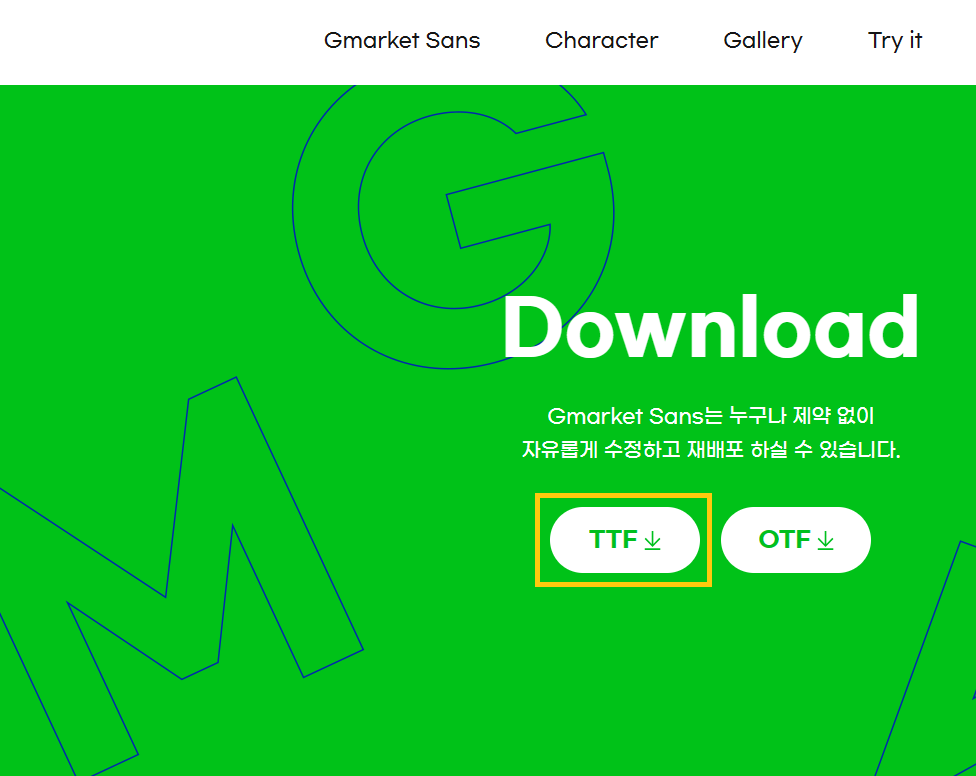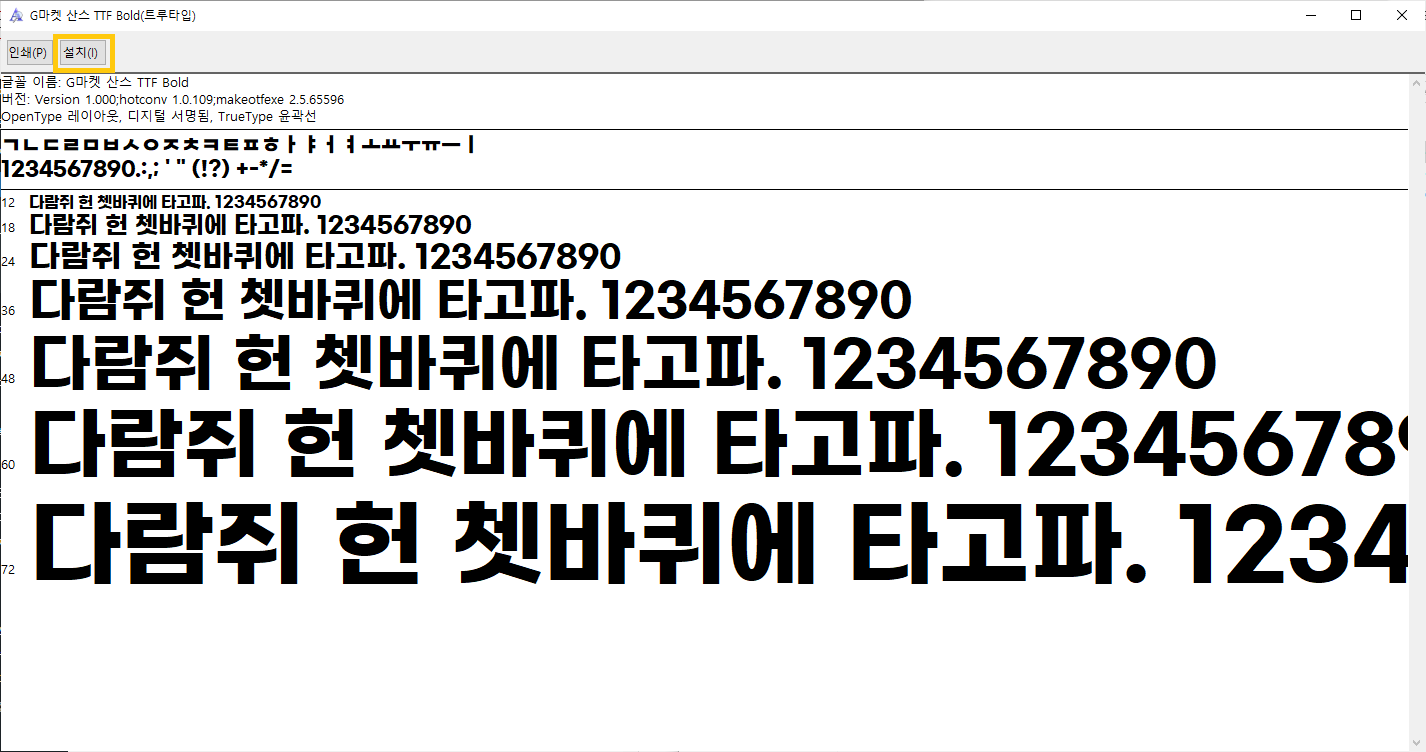
이 글꼴은 G마켓(지마켓)에서 제공하는 브랜드 폰트입니다. 깔끔하고 현대적인 느낌이 드는 폰트입니다. 그래서 여러 곳에 사용하기 좋은 폰트로 추천드립니다. 또한, 제한 없이 사용이 가능하고 또한 상업용으로도 무료입니다. 너무 좋지 않나요? 그뿐만아니라 수정 및 재배포도 할 수 있는 오픈 소스를 기반으로 하는 무료 글꼴입니다.
저는 G마켓 산스 폰트(지마켓 산스 폰트)를 깔끔한 느낌이어서 제목에다가 많이 썼습니다. 사실 제목, 본문 등 어디에 써도 괜찮은 폰트입니다. 또한 기독성이 높은 것이 장점인 것 같습니다.
혹시나 발표 자료를 만들거나 글꼴로 무엇을 만드실 때 G마켓 산스 폰트(지마켓 산스 폰트)를 한 번 사용해 보시는 것도 좋을 것 같습니다.